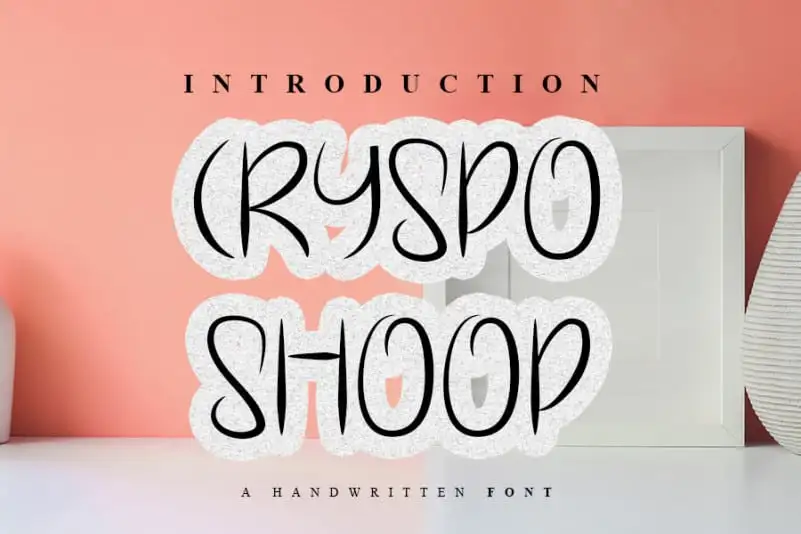
Cryspo Shoop Display Font – Download Grátis
A Cryspo Shoop Display Font é uma excelente escolha para quem busca uma fonte que se destaca tanto por seu estilo original quanto pela sua versatilidade. Esta tipografia manuscrita preserva a elegância tradicional das chamadas enquanto mantém um toque contemporâneo e moderno. Suas características distintivas e fluente permitem usá-la em uma variedade de projetos, desde identidades institucionais até logotipos e materiais de papelaria. Essa fonte é perfeita para quem busca criatividade na sua designação, tornando-a uma opção popular entre os criadores de conteúdo e designers que buscam um visual único em seus projetos digitais ou impressos. Seja você um designer gráfico atento aos detalhes ou alguém buscando adicionar o toque final a seu próximo projeto de escrita formal, Cryspo Shoop Display Font pode ser o parceiro perfeito para sua necessidade criativa.